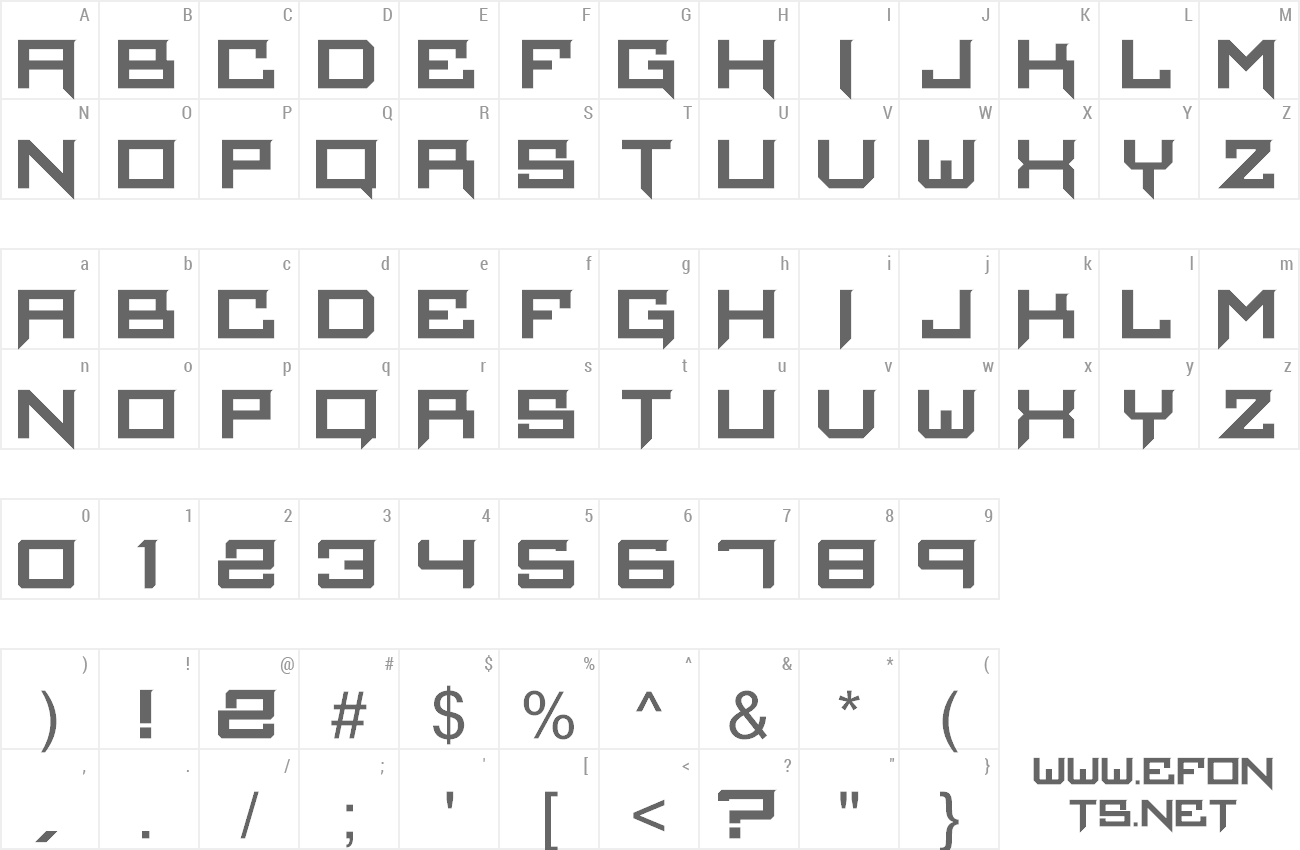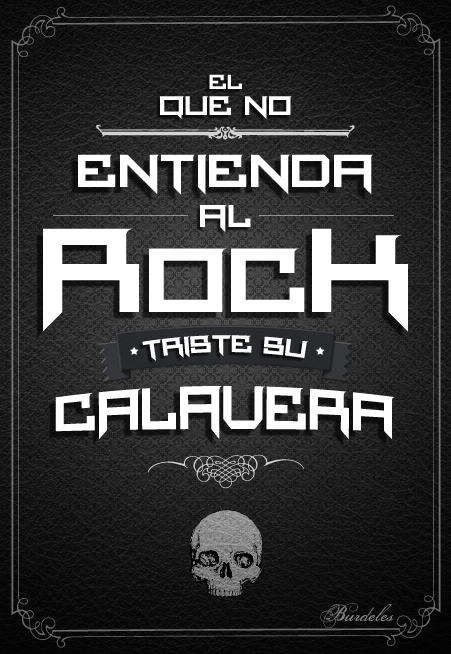
| Font name: | Infierno |
| Author: | Burdeles |
| Note by Burdeles | |
| Tipografia muy pesada y expandida, Preferentemente útil, para pocas palabras, palabras cortas, títulos y logotipos |